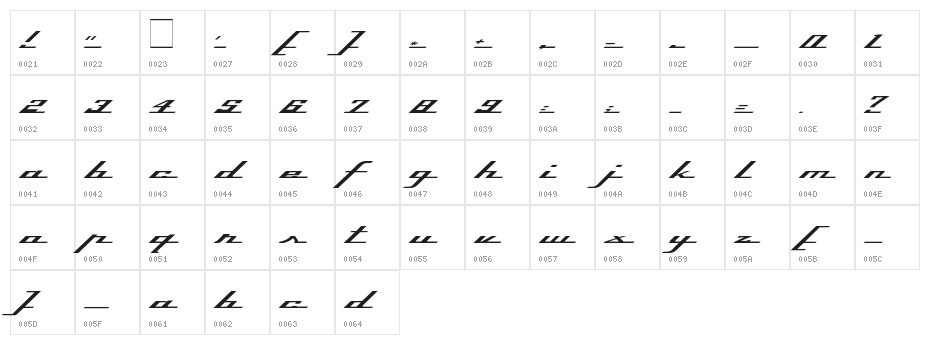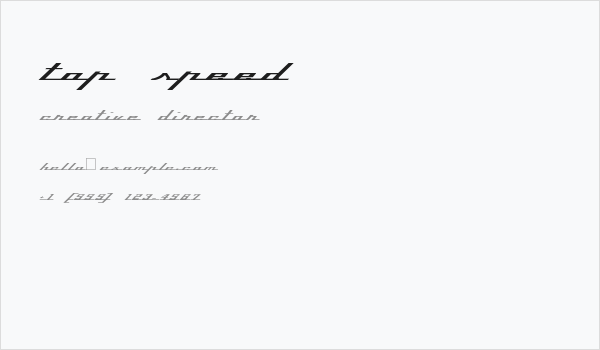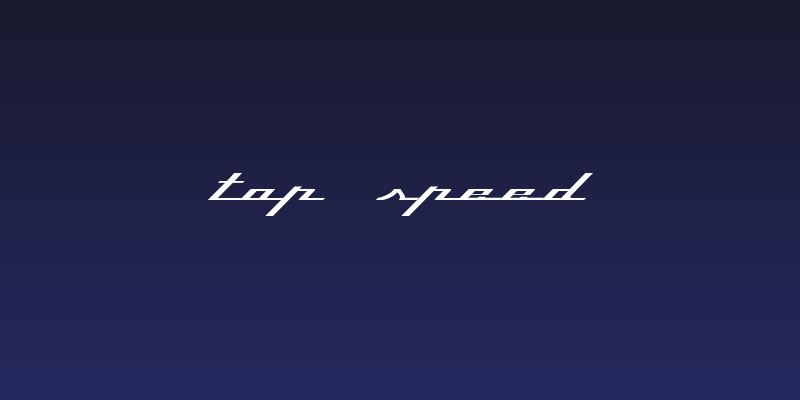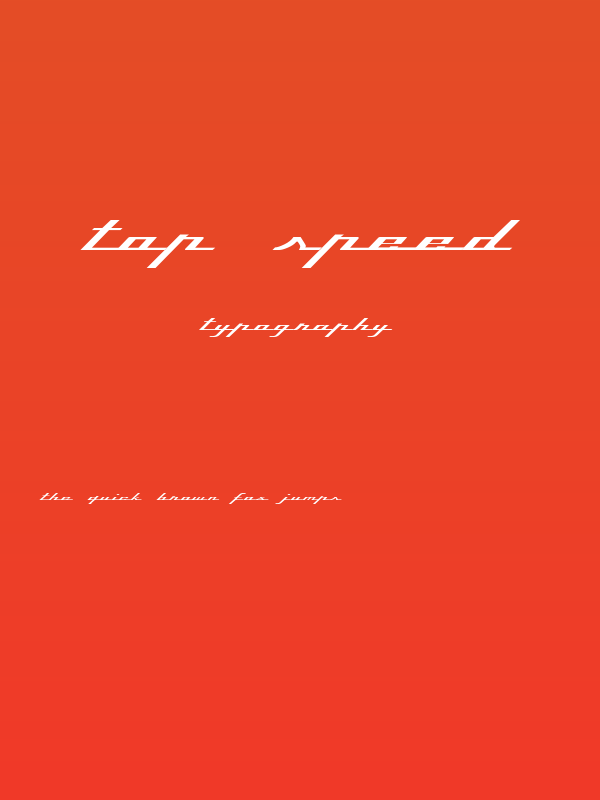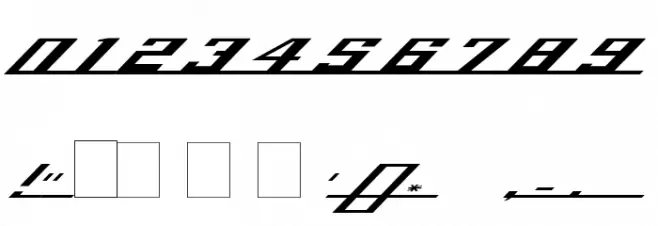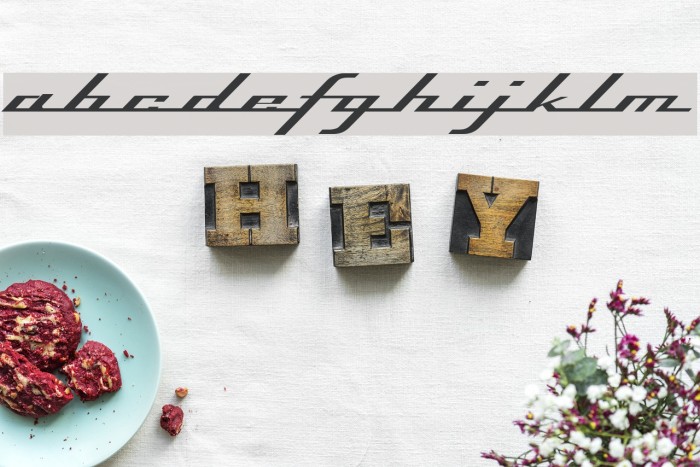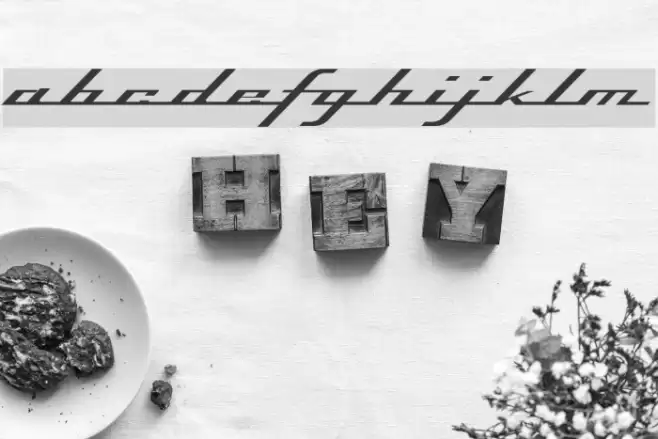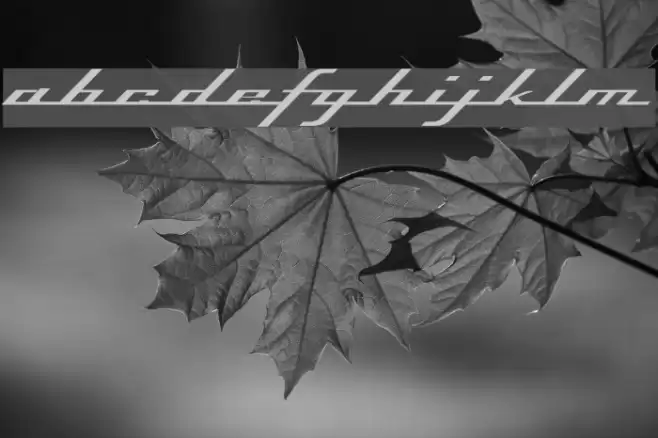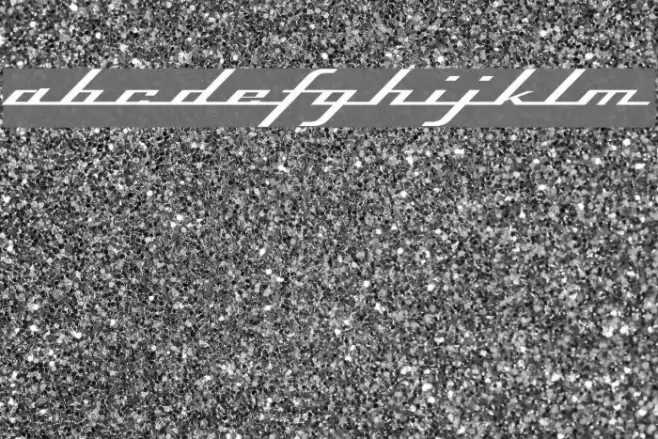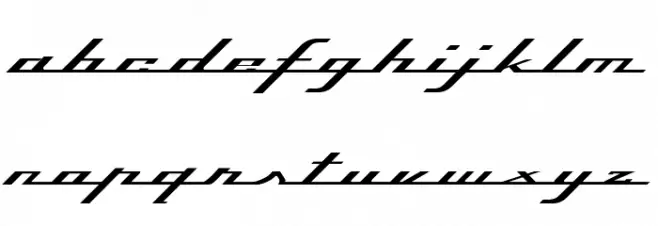
Top Speed Font
✎ Script
| श्रेणियाँ | Script |
| इटैलिक | Yes |
| कंट्रास्ट | High |
| उपयोग का मामला | Logos, Headlines, Posters |
| सुझाए गए प्रोजेक्ट | Ideal for automotive branding, sports team logos, racing event posters, and dynamic product packaging. |